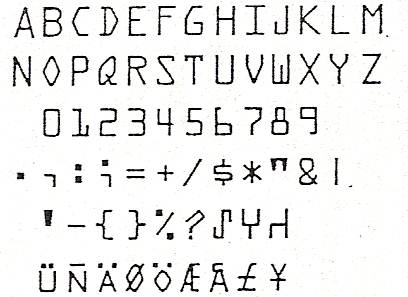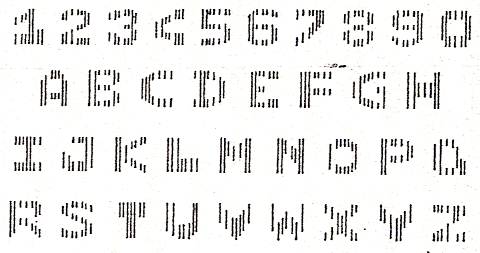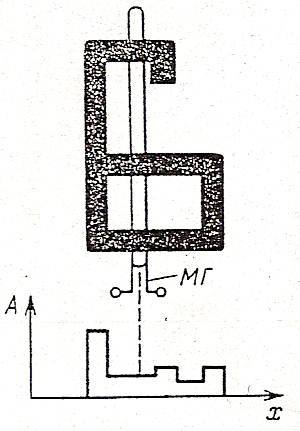
Что из себя представляют стилизованные шрифты, пример
Что из себя представляют нормализованные шрифты, пример. Нормализованные шрифты (НШ).
Предназначены для нанесения изображений символов от руки в строго определенных местах, специально отведенных прямоугольниках. Прямоугольники предварительно печатаются на бланке документа тонкими или цветными линиями, которые не воспринимаются фотодетекторами. Примером служит шрифт для нанесения почтового индекса. Стилизованные шрифты (СШ).
Примеры таких шрифтов для оптического считывания представлены на рис. 5.6б:
Рис. 5.6б для магнитного считывания – рис 5.6в и 5.6г:
Рис. 5.6в
Рис. 5.6г
При считывании шрифта (рис 5.7):
Рис. 5.7 магнитная головка должна перемещаться с постоянной скоростью вдоль строки. Амплитуда сигнала на выходе МГ (магнитной головки) пропорциональна площади магнитных чернил, находящихся под головкой в данный момент времени, т.е. суммарной ширине всех вертикальных отрезков в изображении символа. Полученный сигнал преобразуется в цифровую форму и каждому изображению соответствует фиксированное количество чисел, отображающих амплитуду сигнала. В коде, пример которого приведен на рис. 5.6г, отличительными признаками являются различные расстояния между штрихами, нанесенными магнитными чернилами. Для оптических читающих автоматов наиболее распространенным является стилизованный шрифт РОС-А (ГОСТ 16330 - 70), показанный на рис. 5.6б.